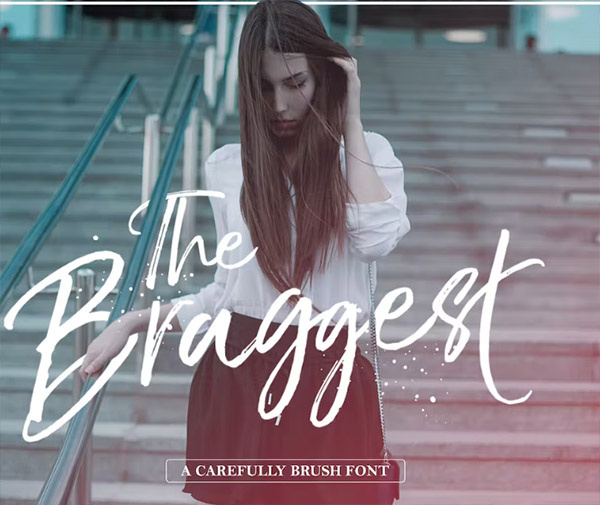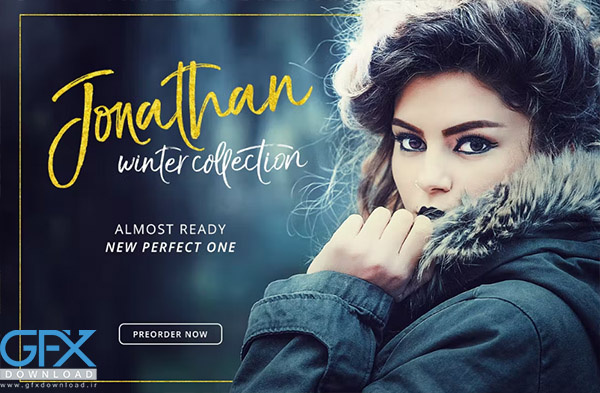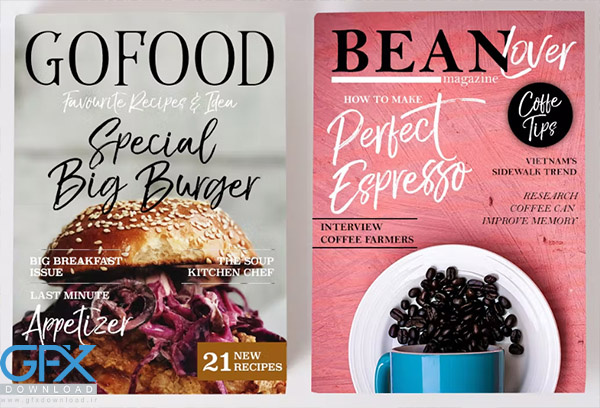
فونت پولی انگلیسی رایگان The Braggest
The Braggest یک فونت جدید با دقت در طراحی که آن را به یک دست خط بسیار شخصی برای هر پروژه تبدیل کرد. فونت پولی انگلیسی رایگان The Braggest شامل دو کاراکتر با حروف کوچک است و به احتمال زیاد پیوندی که به شما امکان می دهد یک دست خط شخصی بخصوص برای پروژه برندسازی بسازید.
این فونت PUA رمزگذاری شده درست مانند فونت های دیگر من، شما نیازی به نرم افزار طراحی خاصی برای دسترسی به کاراکتر جایگزین ندارید، می توانید به کاراکتر جایگزین دسترسی داشته باشید، شامل کاراکتر های جایگزین و لیگاتور عالی و پشتیبانی چند زبانه. این فونت از 33 زبان مختلف پشتیبانی می کند: آلبانیایی، کرواتی، چکی، مجارستانی، لهستانی، رومانیایی، صربی (لاتین)، اسلواکی، اسلوونیایی، آفریقایی، باسکی، کاتالان، دانمارکی، هلندی، انگلیسی، فاروئی، فنلاندی، فرانسوی، گالیسی، آلمانی، ایسلندی، اندونزیایی، ایتالیایی، مالایی، نروژی، پرتغالی، اسپانیایی، سواحیلی، سوئدی، ترکی، استونیایی، لیتوانیایی.